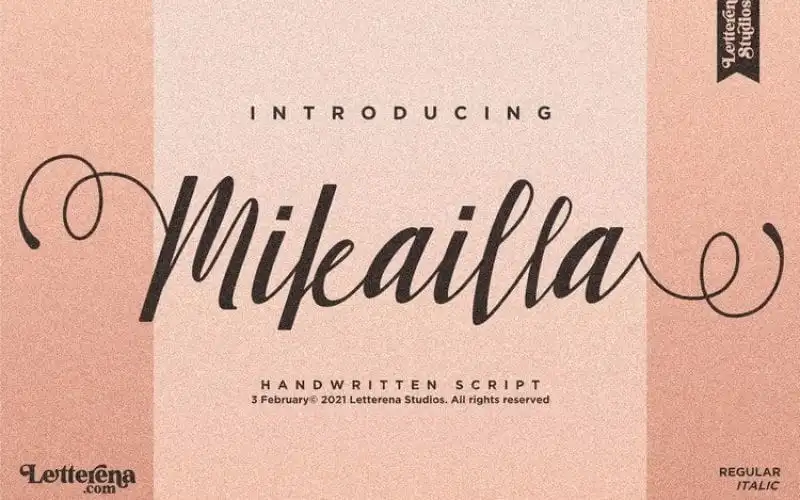
A Mikailla Calligraphy Font é uma elegante e sofisticada fonte script projetada para representar formalidade e qualidade premium nos seus trabalhos. Esta fonte é perfeitamente adequada para um vasto range de projetos, desde logotipos e identidades corporativas até designs de embalagens, camisetas e revistas. Ideal também para cartões personalizados, convites e cartas festivas, etiquetas e mesmo para a criação de fotografias com um toque especial. A Mikailla Calligraphy Font é uma escolha perfeita para quem busca dar um toque distintivo em qualquer projeto que precise de um toque de elegância. Seja para personalizar uma embalagem ou criar cartões de visita, a Mikailla Calligraphy é um recurso gráfico que se encaixa com fluidez e conforto nas várias aplicações necessárias. A sua versatilidade faz da Mikailla Calligraphy Font o perfeito complemento para qualquer projeto em que deseje agregar uma qualidade premium de design.